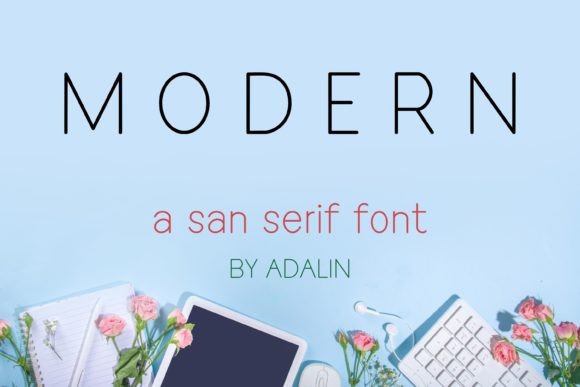
Modern
Modern : la police sans‑serif qui donne du style à tous vos produits
Vous cherchez une typographie moderne, polyvalente et ultra‑lisible pour vos emballages, vos campagnes publicitaires ou vos interfaces digitales ? Ne cherchez plus : Modern Sans Serif répond à toutes ces exigences. Conçue pour s’adapter à tous les secteurs – alimentation, boissons, équipements de bureau, construction, mode, chaussures – cette police apporte une touche contemporaine sans jamais sacrifier la clarté.
Pourquoi Modern se démarque ?
- Design épuré : des lignes nettes et des courbes équilibrées qui confèrent une impression de professionnalisme instantanée.
- Lisibilité optimale : chaque glyphe est étudié pour être lisible même à petite taille, idéal pour les étiquettes de produits alimentaires ou les numéros de série d’équipements.
- Adaptabilité sectorielle : que ce soit pour un packaging de boisson énergisante ou la signalétique d’un chantier, Modern s’ajuste sans effort.
- Impact visuel fort : son style sans‑serif renforce l’image de marque moderne et dynamique que recherchent les marques de mode et de chaussures.
Comment intégrer Modern dans vos projets
En résumé, Modern Sans Serif est la solution typographique idéale pour les entreprises qui souhaitent allier esthétique contemporaine et performance fonctionnelle. Adoptez-la dès aujourd’hui et donnez à vos produits l’apparence professionnelle qui attire les consommateurs et booste votre visibilité en ligne.